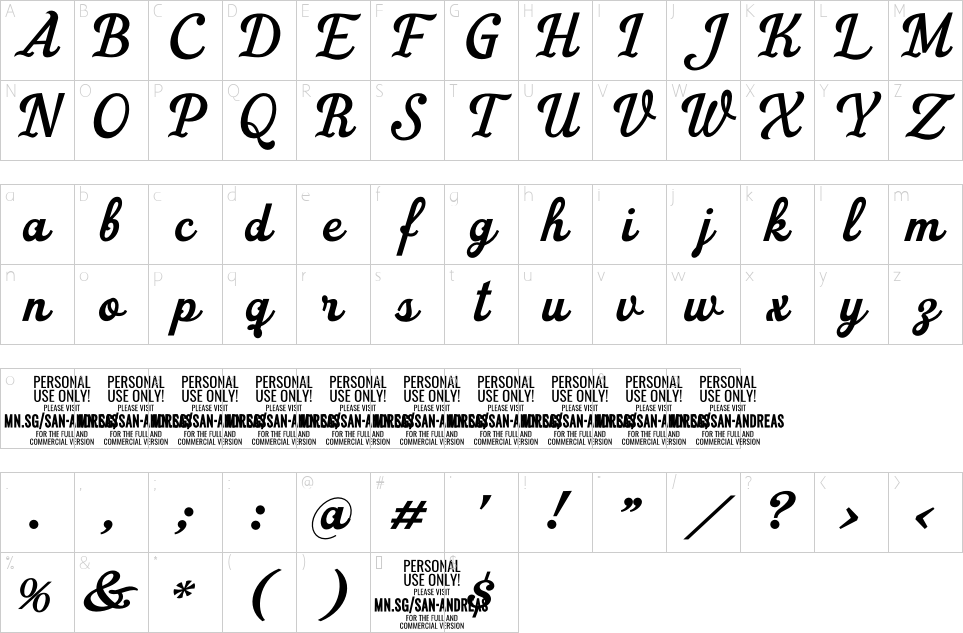
A San Andreas Font é uma opção gratuita e poderosa para adicionar um toque único a seus projetos digitais. Desenvolvida pelo designer Måns Grebäck, esta fonte está disponível tanto para Windows quanto para Mac. Com suas linhas elegantes e clara tipografia, a San Andreas é perfeita para quem busca um estilo moderno e minimalista em seus materiais. Foi baixada 192 vezes, o que mostra o quanto os designers apreciam sua facilidade de uso e variedade de opções de estilo. Se você está procurando por uma fonte que não apenas é gratuita, mas também de alta qualidade, a San Andreas é uma escolha excelente. Descubra por si mesmo a diferença que esta font faz em seu trabalho.